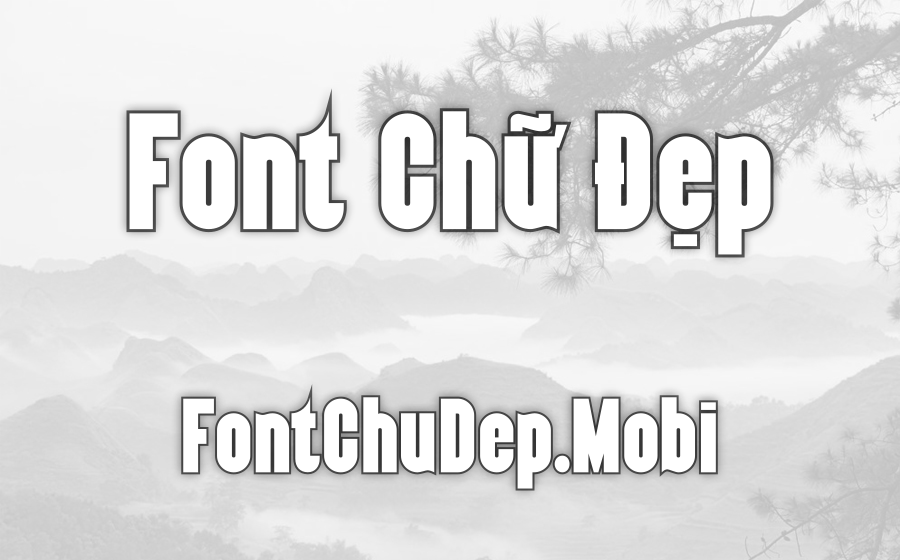
Font DL Almonte Việt Hóa
DL Almonte Regular
Gần đây, tôi đã thử nghiệm một kiểu chữ độc đáo tên là Almonte, và phải nói rằng tôi hoàn toàn bị cuốn hút bởi vẻ đẹp cổ điển mà nó mang lại. Được tạo ra bởi nhà thiết kế tài năng Ray Larabie, kiểu chữ này như một làn gió mát với phong cách trang trại mộc mạc, gợi nhớ đến kết cấu của gỗ, mang lại sự ấm áp và cảm giác hoài cổ vô cùng đặc trưng. Một điều đặc biệt mà tôi rất thích ở Almonte chính là khả năng phù hợp với nhiều chủ đề thiết kế khác nhau, như nông thôn, steampunk hay những ý tưởng liên quan đến lịch sử sáng tạo.
Người dùng Việt giờ đây càng có nhiều lý do để yêu thích nhờ việc Almonte đã được Việt hóa bởi Tduy, mở rộng hỗ trợ cho nhiều ngôn ngữ khác. Đây thực sự là một tin vui cho những ai yêu thích sáng tạo và muốn đa dạng hóa các tác phẩm của mình. Điều thú vị hơn là font chữ này được thành viên của FontChuDep.mobi sưu tầm và chia sẻ, giúp cộng đồng thiết kế có thể dễ dàng tiếp cận và áp dụng vào các dự án.
Về mặt thiết kế, Almonte nổi bật với các ký tự dày dặn, rất mạnh mẽ và đầy sức hút, lý tưởng cho những ai cần tạo điểm nhấn trong các thiết kế tiêu đề, poster hoặc logo. Đặc biệt, tôi thấy nó rất hữu ích cho các ngành nghề như quảng cáo, ẩm thực, thiệp cưới và các sản phẩm cần sự nổi bật như bao bì hay ấn phẩm truyền thông. Không chỉ vậy, Almonte còn là lựa chọn lý tưởng cho các dịp đặc biệt như lễ hội, sinh nhật, Halloween, hay Trung thu, mang lại một dấu ấn khó quên cho các sự kiện này. Thật sự, trải nghiệm với Almonte đã mở ra cho tôi nhiều cảm hứng sáng tạo mới mẻ!